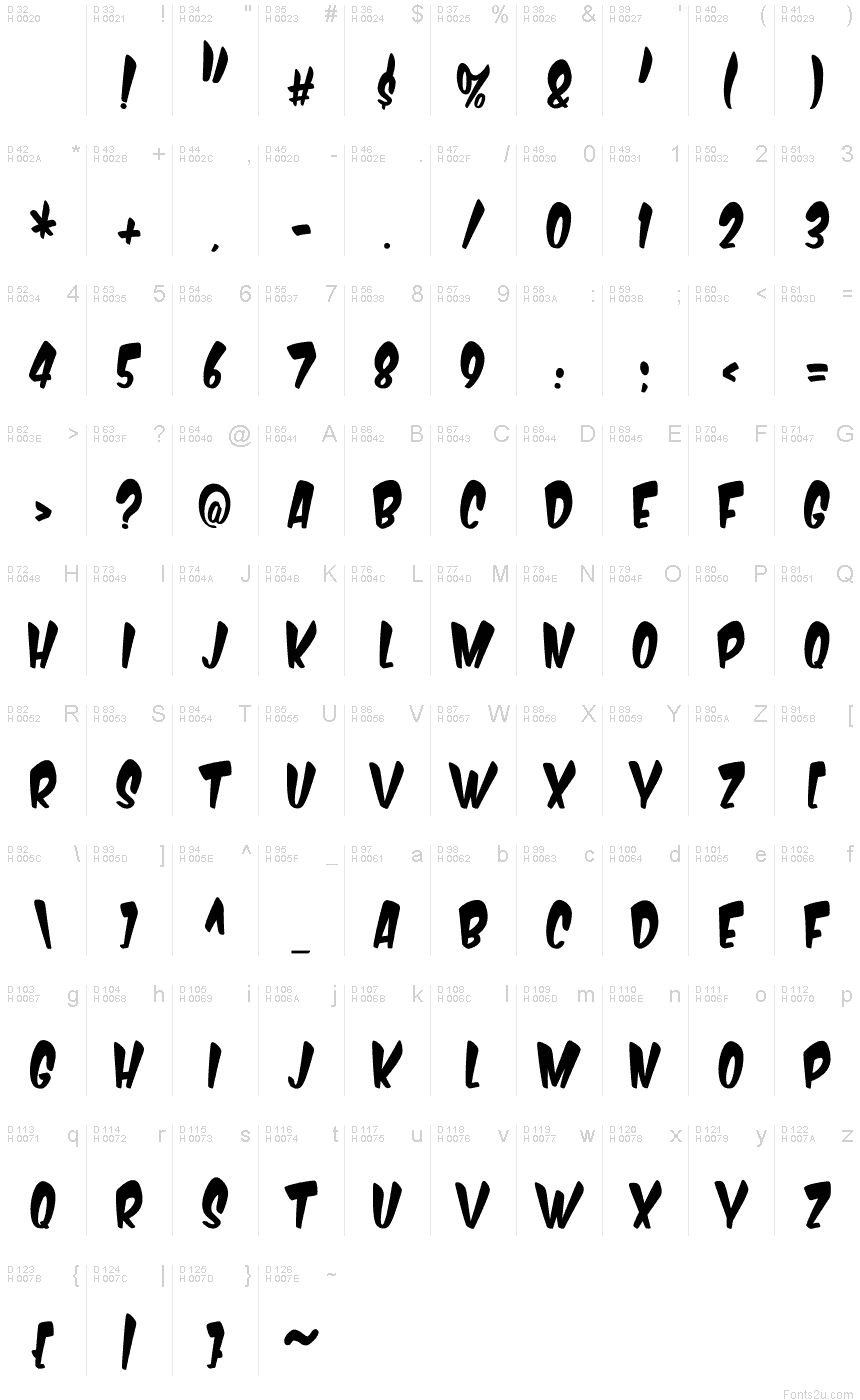
Komika Title - Boogie von WolfBainX und Apostrophic Labs ist eine kostenlose Comic-Display-Schrift mit klobigen, handgezeichneten Buchstaben. Breite Striche schwellen an und laufen in scharfe Spitzen aus, während unregelmäßige Winkel die Formen in Bewegung halten. Die Buchstaben drängen mit lebendiger Kraft eng zusammen.
Ihr offensichtliches Zuhause ist die Comic-Branche, insbesondere für Titelbilder und Aktionsbildunterschriften. Dieselben federnden Silhouetten passen zu Arcade-Grafiken, Fanartikeln und Snack-Verpackungen mit einem ungezügelten Cartoon-Thema. In diesen Umgebungen kann die Schrift eher Teil eines illustrierten Explosionsmotivs oder Maskottchen-Emblems als neutraler Text werden.
Komika Title - Boogie